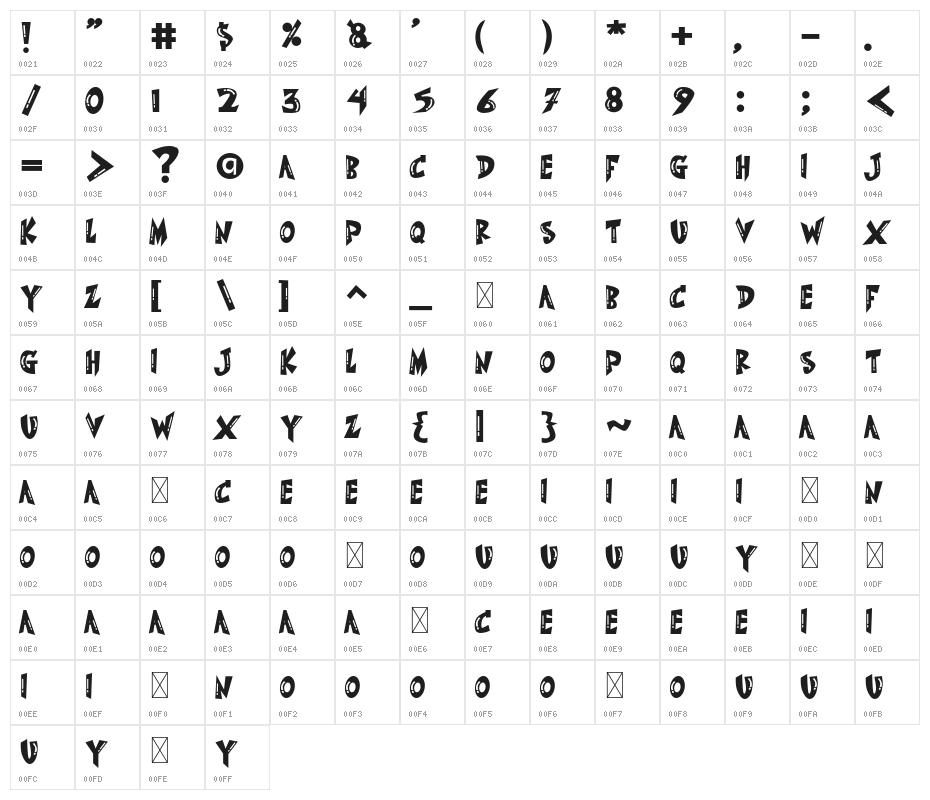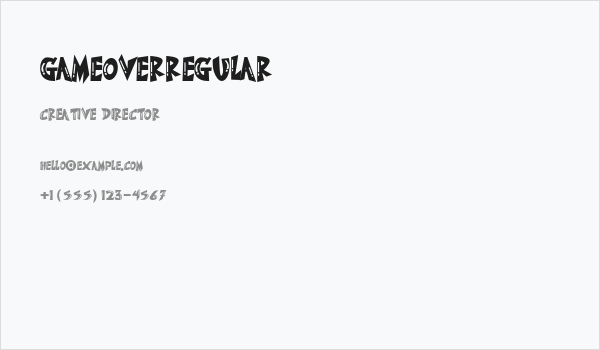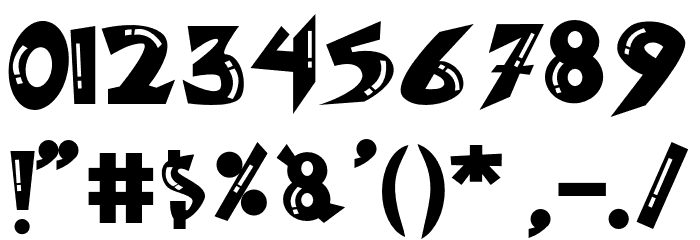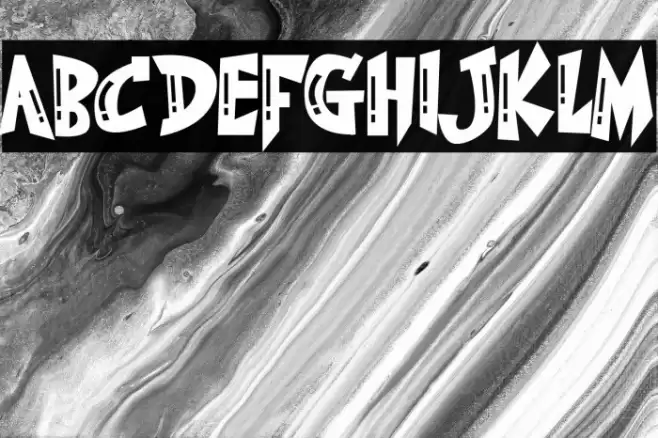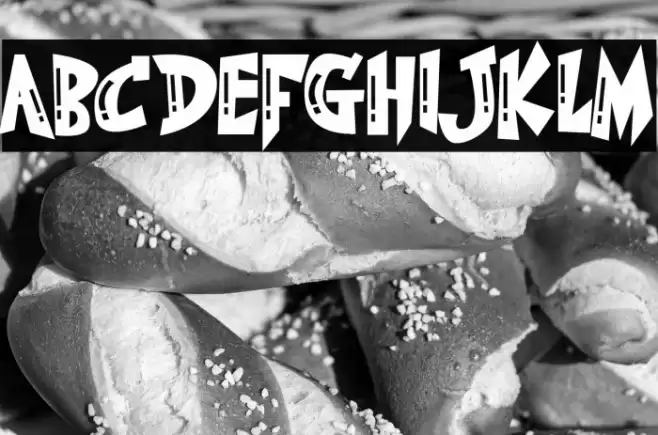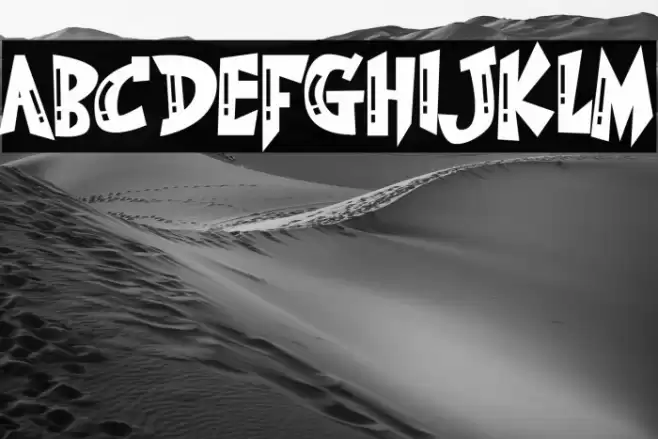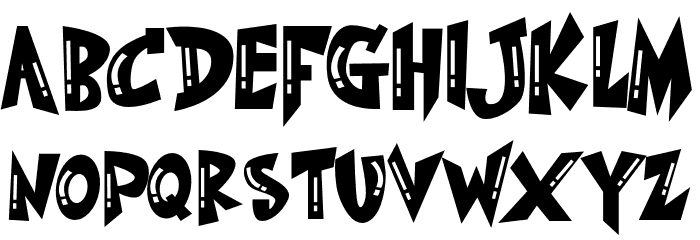
GameOverRegular Font
✎ Cartoon
Fonts by Eddy Goodboy
| 字体家族 | Game Over |
| 分类 | Cartoon |
| 整体风格 | Playful, Cartoonish |
| 推荐项目 | Ideal for video game titles, children's books, posters, and any project needing a fun, energetic typeface. |